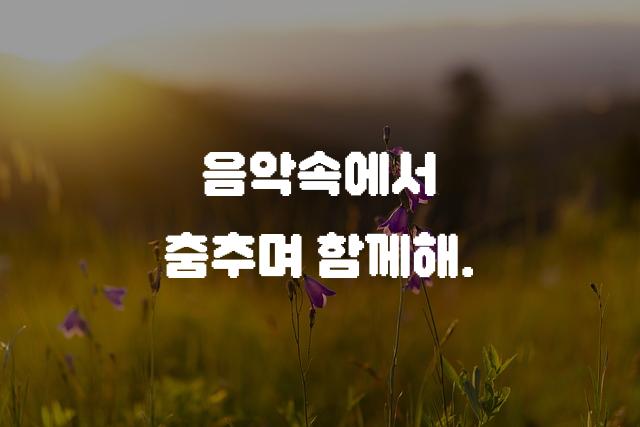
던파 연단된 칼날은 (주)네오플에서 제작한 바탕체 명조 폰트로, 각진 형태의 디자인이 특징입니다. 클래식하면서도 판타지적인 느낌을 주어 다양한 문화 콘텐츠에 잘 어울립니다.
던파 연단된 칼날은(는)
바탕 스타일, 명조/전통, 네모꼴, 복고풍, 게임 느낌, 단단함 계열의 생김새를 가지고 있으며
로고 디자인, 광고 캠페인, 웹/앱 디자인 등에서 자주 활용되며, 효과적인 메시지 전달에 적합합니다.
이 폰트는 광고/마케팅, 크리에이티브, 엔터테인먼트 분야에 잘 어울리며,
세련된, 창의적인, 강렬한 느낌을 담고 있는 것이 특징입니다.